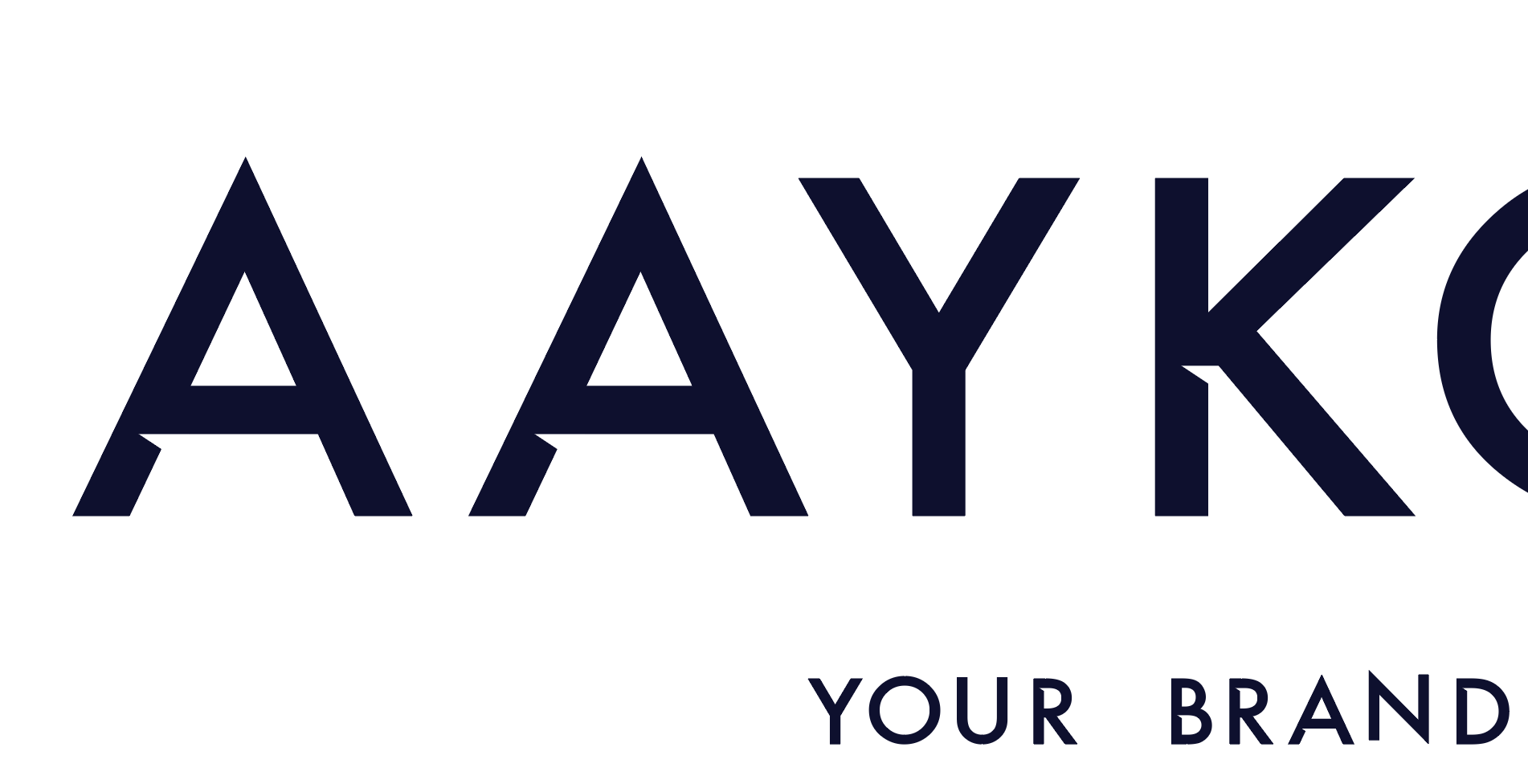
Kennt jemand diese Schrift? (Freepick)
Ich habe mir eine .ai Datei bei Freepick mit dieser Schrift gekauft. Da ich sie gerne auch als "normale" Schriftart verwenden wollte, wollte ich wissen, welche Schrift das sein könnte, da sie mir wie gesagt nur als Vectordatei vorliegt. Danke
Sieht mir nach einer bearbeiteten Futura Medium aus.